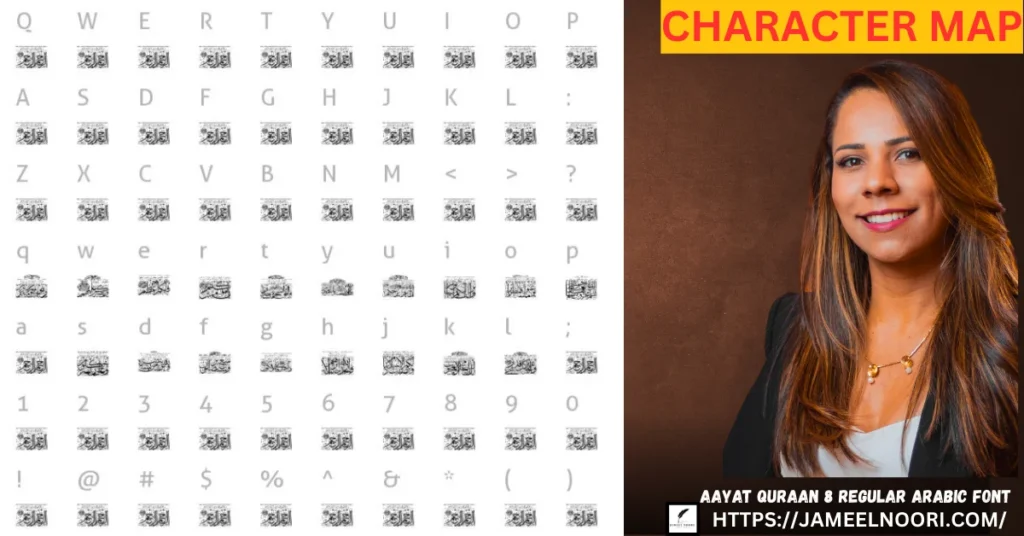
Aayat Quraan 8 Regular Arabic Font aik khubsurat aur professional Arabic typeface hai jo khas tor par Quranic text, Islamic content aur Arabic calligraphy ke liye design kiya gaya hai. Ye font Pakistan, Lahore, Karachi aur duniya bhar ke users ke liye ek behtareen choice hai jo Urdu fonts, Arabic fonts, aur Quran writing ke liye readable solution chahte hain.
Features of Aayat Quraan 8 Regular Arabic Font
Is font ka Character Map bhi available hai jahan se aap har letter ki calligraphy aur ligatures easily samajh sakte hain.
What Makes Aayat Quraan 8 Regular Arabic Font a Best Choice?
Aayat Quraan 8 Regular Arabic Font apni clean calligraphy aur balanced letter spacing ki wajah se ek expert choice mana jata hai. Ye font specially Quran verses likhne ke liye optimize kiya gaya hai jahan har harf ki clarity bohat ahm hoti hai.
Iska structure traditional Arabic writing rules ko follow karta hai, jis se reading experience smooth rehta hai. Pakistan ke madaris, Islamic websites aur designers isay regularly use karte hain. Agar aap best arabic font ya arabic font download search kar rahe hain, to ye ek reliable option hai.
Best Uses of Aayat Quraan 8 Regular True Type Arabic Font in Pakistan
Aayat Quraan 8 Regular Arabic Font ka use sirf Quran tak limited nahi hai. Ye multiple professional aur religious projects ke liye suitable hai.
Common Use Cases:
- Quran printing & digital Quran apps
- Islamic books & tafseer
- Mosque banners & posters
- Arabic learning material
- Urdu & Arabic mixed content websites
Agar aap Urdu fonts aur Arabic fonts ko ek sath professionally use karna chahte hain, to ye font aapke content ko visually strong banata hai.
Why Designers Prefer Aayat Quraan 8 Regular Arabic Font
Professional designers is font ko is liye prefer karte hain kyun ke ye readability aur aesthetics dono ko balance karta hai. Long Quranic text me aankhon par pressure nahi padta aur har harf wazeh nazar aata hai.
Aayat Quraan 8 Regular Arabic Font ek trusted aur professional Arabic font hai jo Quranic aur Islamic content ke liye perfect hai. Agar aap Pakistan me reh kar arabic font download, best arabic font, ya high-quality religious typography search kar rahe hain, to ye font aapki expectations par pura utarta hai. Proper spacing, authentic calligraphy aur wide compatibility isay ek ultimate choice banati hai.
Is this font suitable for Quran writing?
Yes, it is specifically optimized for Quran verses and Islamic content.
Why is this font popular in Pakistan?
Because of its clarity, Quran compatibility, and easy readability.